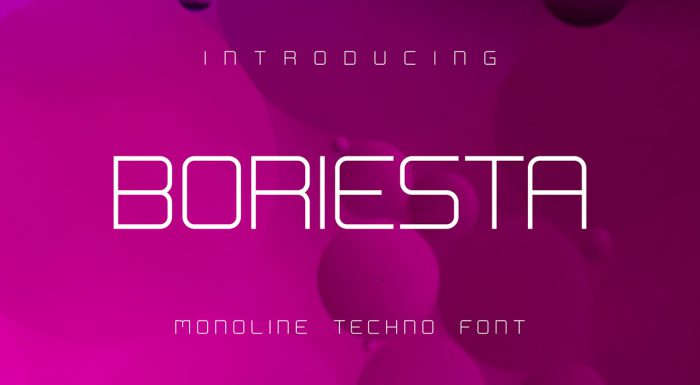
فونت Boriesta انگلیسی
دانلود فونت Boriesta انگلیسی Font بوریستا |
| ⭐ مجموعه فونت | دانلود فونت انگلیسی بوریستا Font Boriesta |
| ⭐ توضیحات | فونتی مناسب برای توصیف محصولات در قالب تکنولوژی، دنیای ربات ها، بازی های بیلیارد، ماشین آلات، الکترونیک و مواردی از این دست. این فونت نازک ساخته شده است و برای توضیحات محصول در نظر گرفته شده است، نه برای نمایش محصول اصلی.
می تواند یک فونت پشتیبانی جایگزین از فونت اصلی باشد، البته مربوط به دنیای تکنولوژی. |